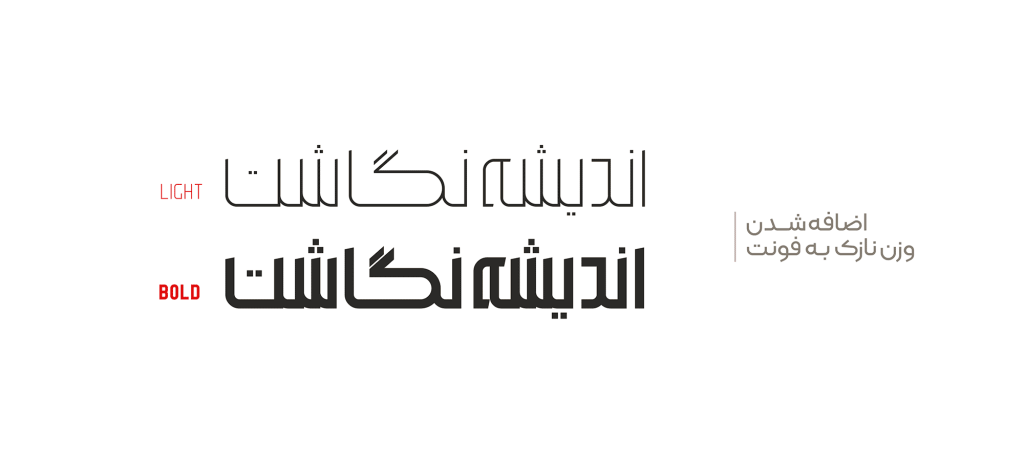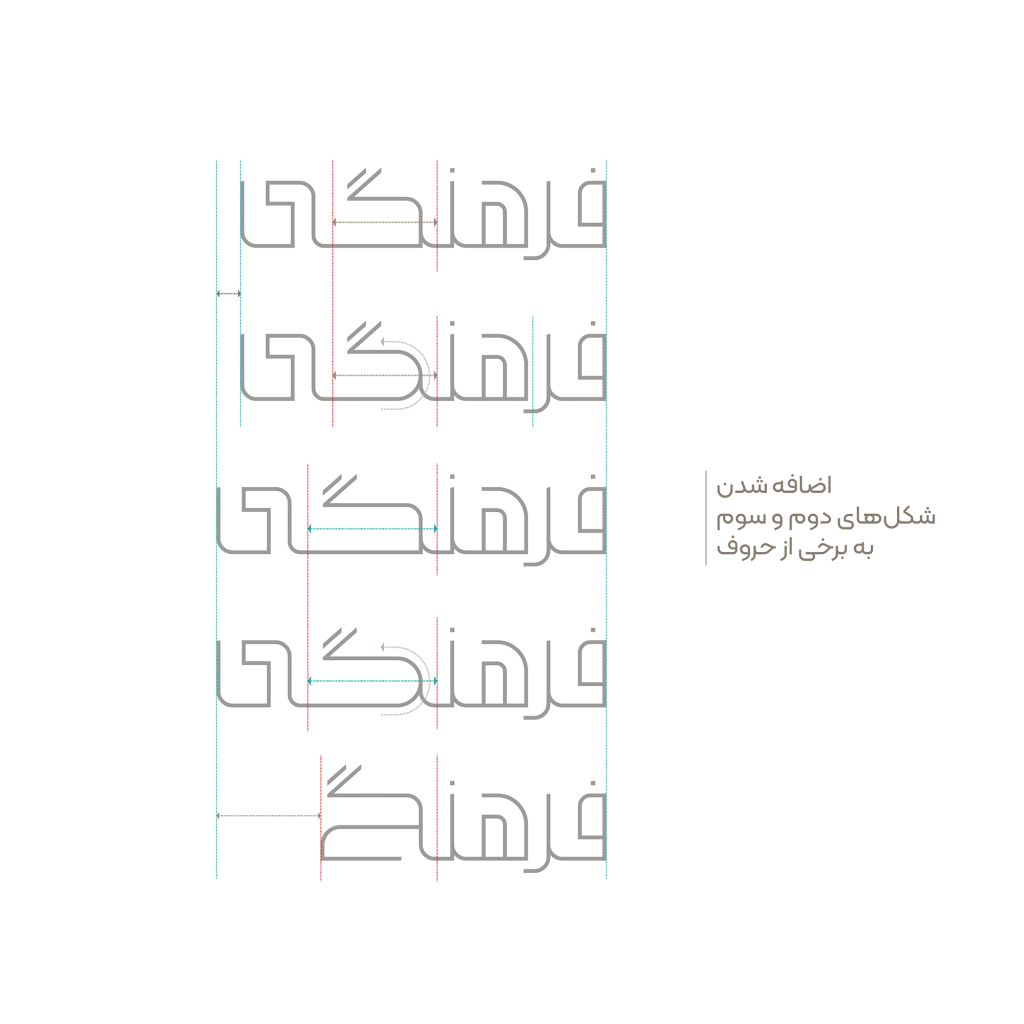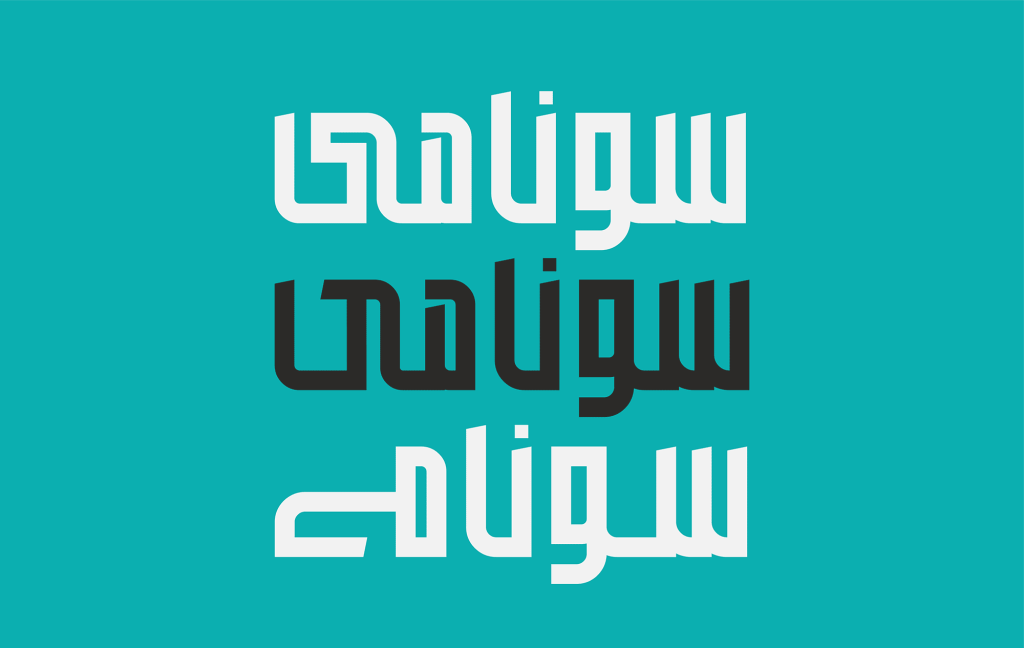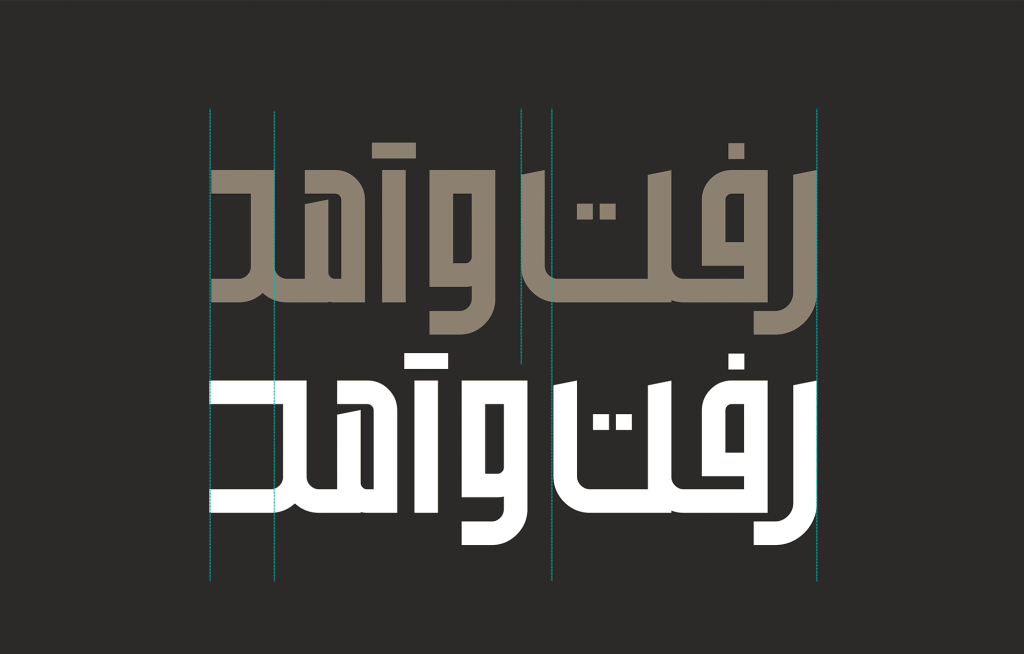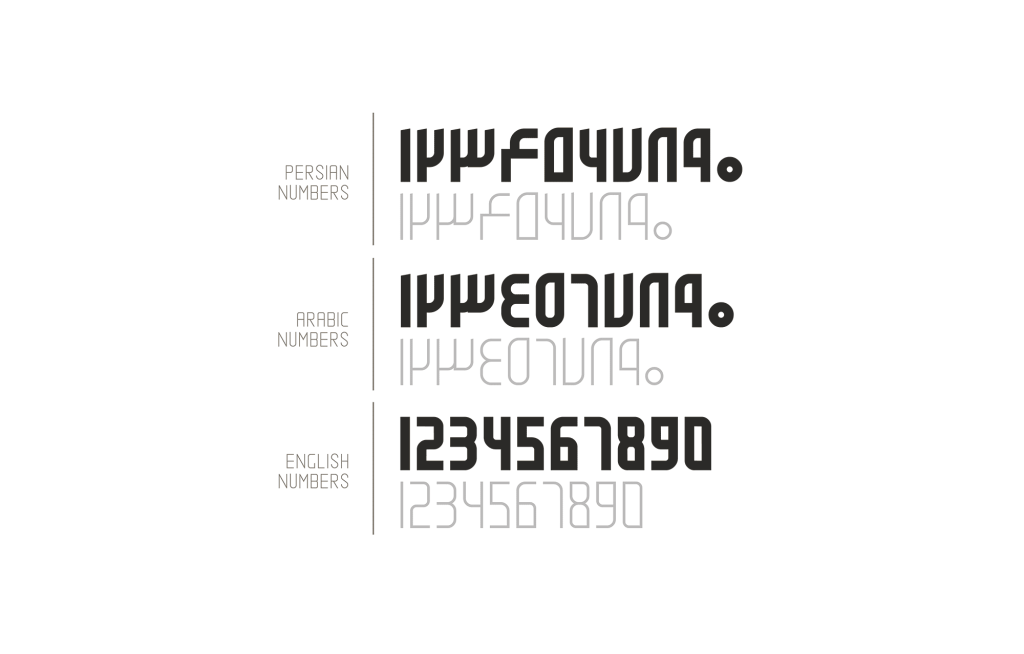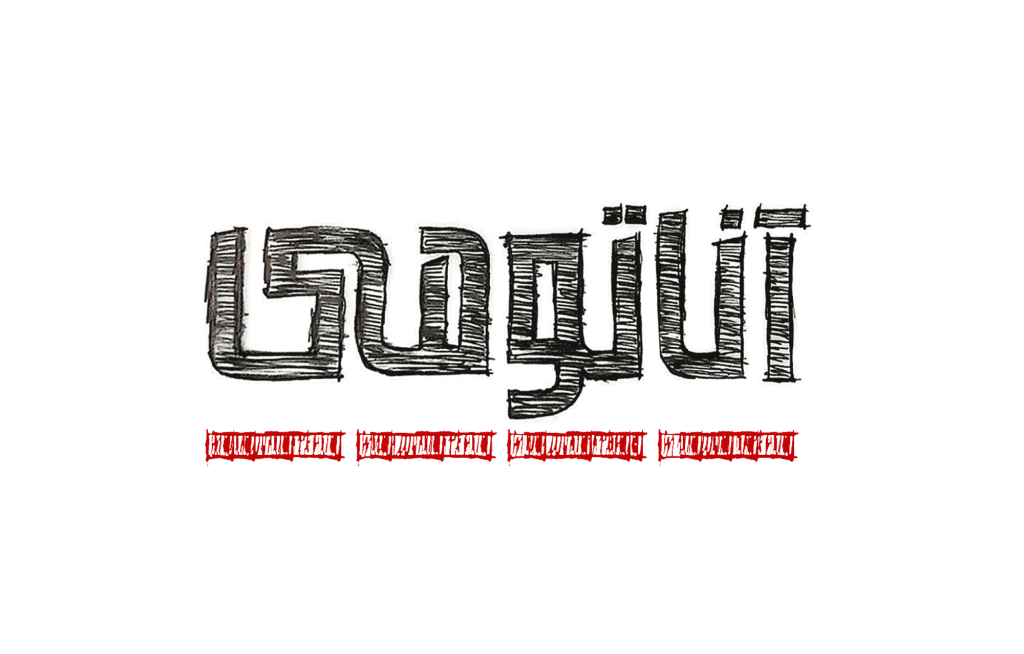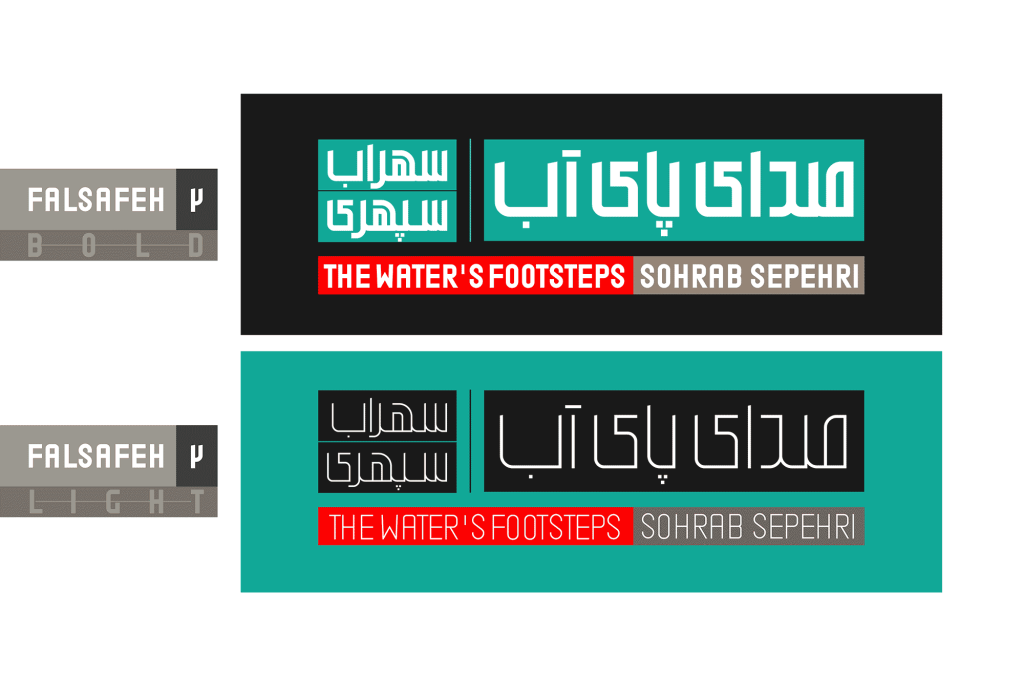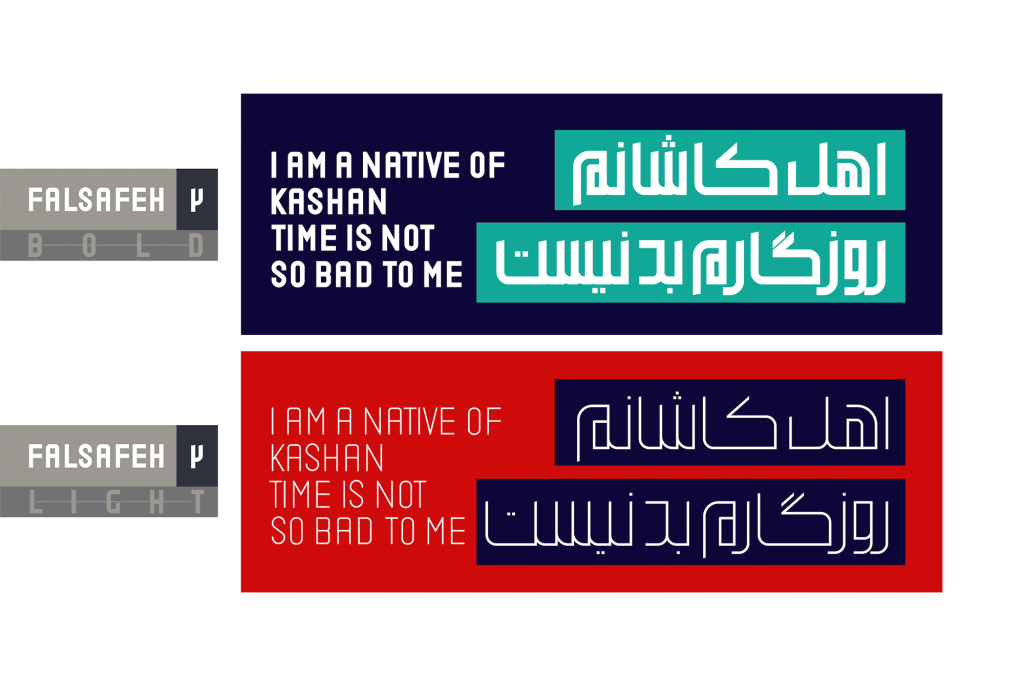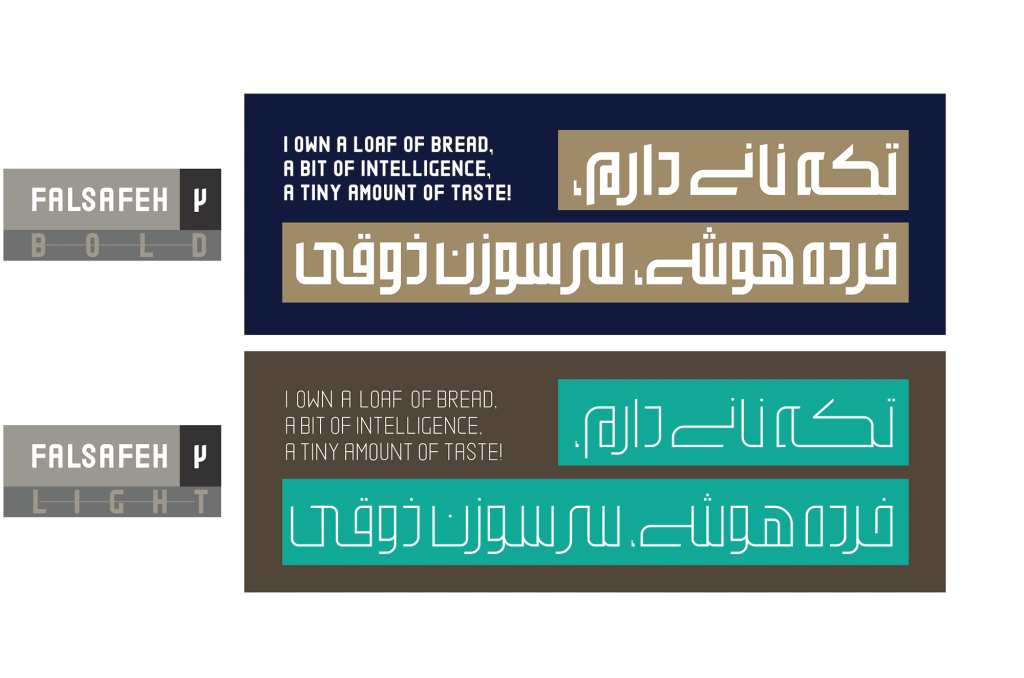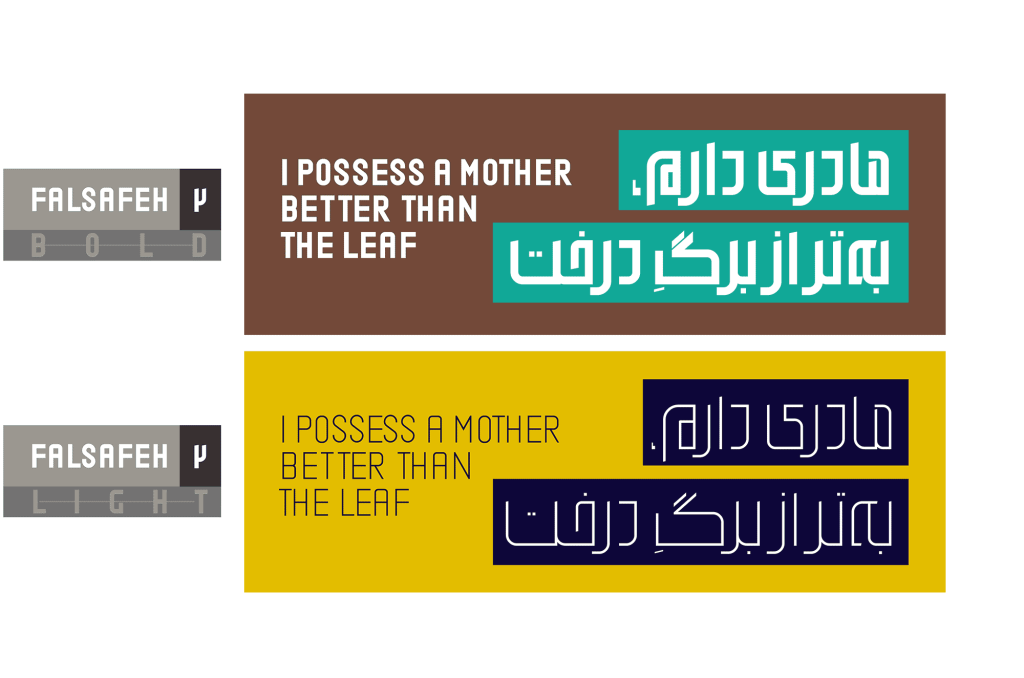
فونت فلسفه قلمی از خانواده هندسی مناسب برای متون کوتاه و عناوین می باشد . اصلی ترین ویژگی آن ماندکاری در ذهن خواننده است به سبب فرم طراحی این تایپ فیس خاص و ویژه ای که دارد.
فونت فلسفه مناسب برای تیتر های تبلیغاتی
فونت فلسفه قلمی از خانواده هندسی که طراح آن آقای کریم عامری با تلاش برای این هدف و مقصود که تایپ فیسی طراحی شود تا ذهن مخاطب را به چالش کشیده و جذب خود نماید. همین ویژگی یعنی جذب و در گیر کردن نگاه خوانندگان سبب نمایشی بودن این فونت و کاربرد آن در متون کوتاه و عناوین می باشد.
این قلم مناسب متون ریز و طولانی نیست و برای انواع تیتر های تبلیغاتی و مطبوعاتی از چاپ و نشر گرفته تا تولید و محتوا در حوزه وب بسیار مناسب می باشد. فونت دلنیا از نقطه نظر هم خانوادگی و شباهت فصل مشترک های بسیاری با این تایپ فیس دارد. در صورت تمایل به این سبک از تایپ فیس های فارسی می توانید به مشاهده دلنیا نیز بپردازید.
فلسفه قلمی مانا و ماندگار
همانطور که پیش تر نیز گفته شد یکی از اهداف اصلی فلسفه ایجاد نگرشی نو و به چالش کشیدن ذهن مخاطب با نوشته است. هنگامی که خواننده‌ی یک متن برای خواندن آن دچار چالش می‌شود، متن در ذهن او ماندگارتر و مانا تر می‌شود و همانطور که می دانیم این تاثیر یکی از مهم‌ترین نتایج انتقال بسیاری از پیام‌ها به خصوص پیام‌های تبلیغاتی می باشد.
فلسفه دارای شخصیتی با ثبات و پر صلابت است . که از قدرت نمایشی خاصی بهره می برد. در زیر تصاویری نمونه از این قلم برای شما عزیزان ارائه گردیده است که می توانید مشاهده کنید.